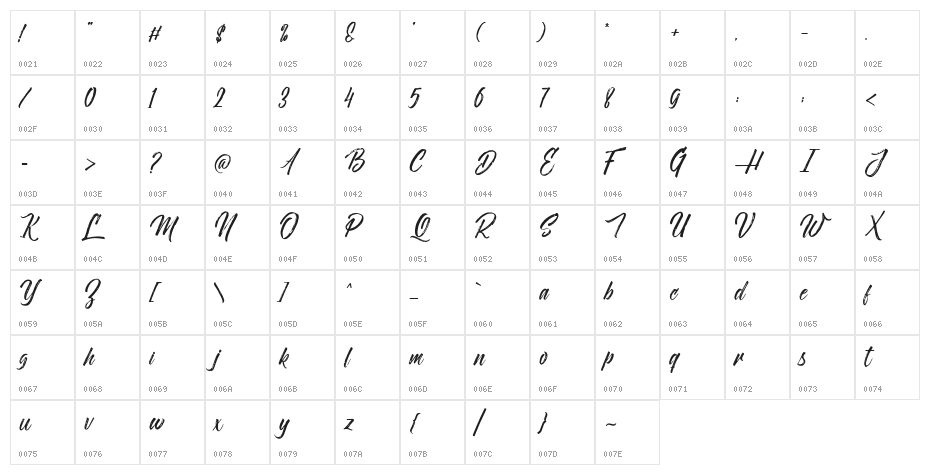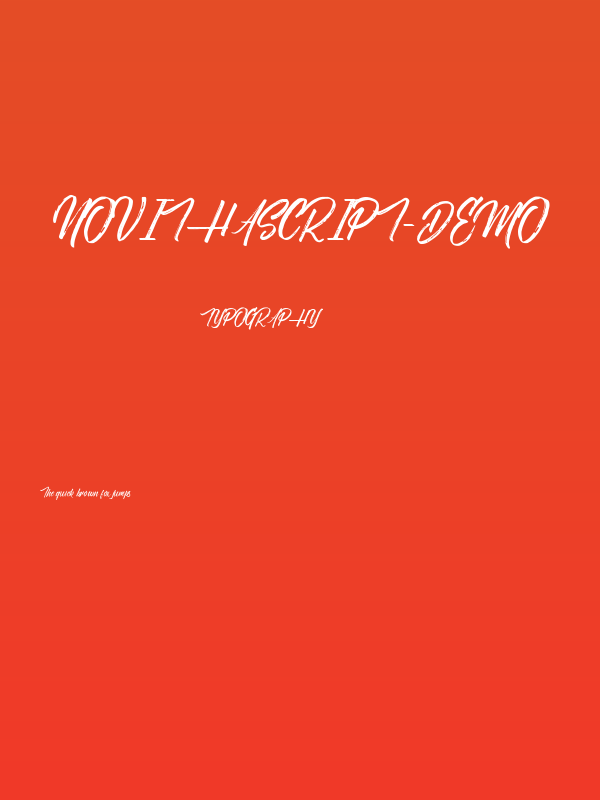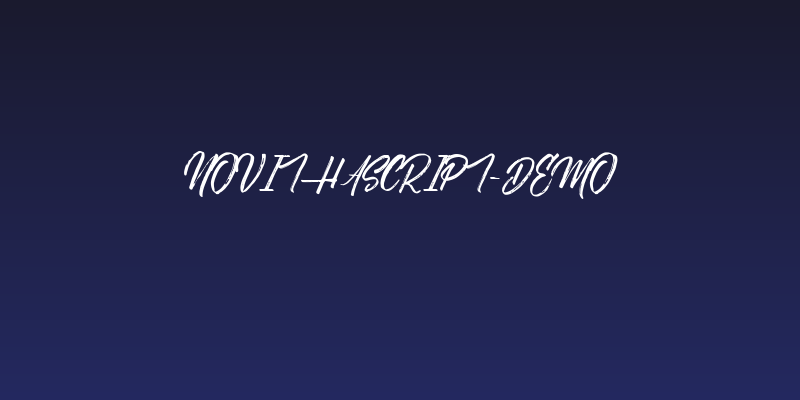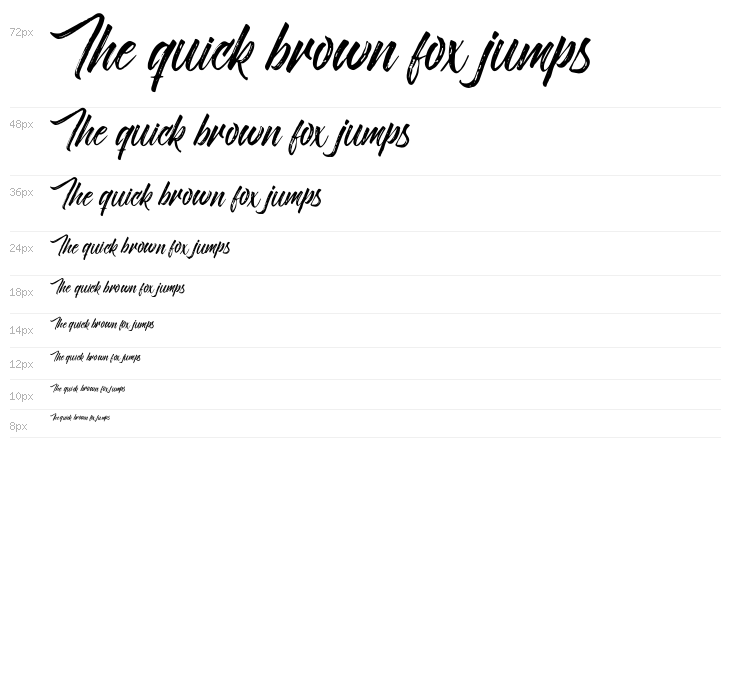
NovithaScript-Demo Font
| Caso d'uso | Logos, Headlines, Invitations |
| Progetti proposti | Ideal for wedding invitations, greeting cards, logos, branding, and other creative projects requiring a personal touch. |